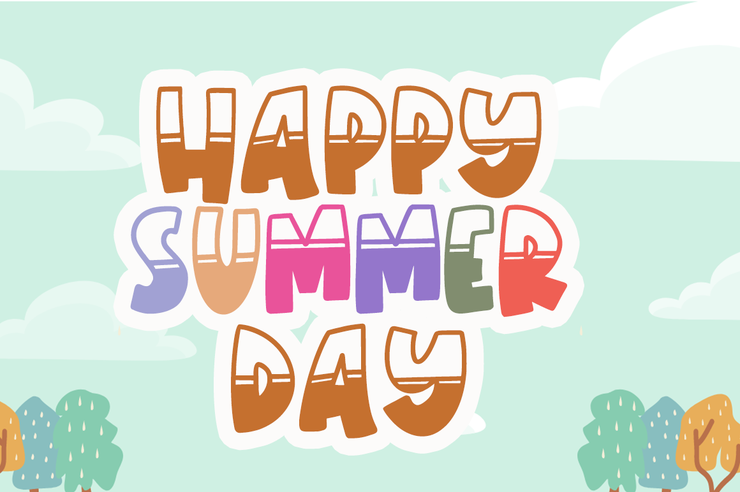
Birthday ist eine lebendige, dekorative englische Schrift mit verspielten Kurven und festlichen, glatten Strichen. Sie verfügt über helle, warme und fröhliche visuelle Effekte, die perfekt zu Geburtstagsfeiern, Jubiläen und fröhlichen Festszenen passen. Diese charmante Schrift ist ideal für Geburtstagseinladungskarten, Partyposter, Geschenkverpackungsetiketten, Grafiken für Konditoreien, Geburtstagsinhalte in sozialen Medien, Veranstaltungsbanner und dekorative Typografie für Feiertage. Komplett mit Groß- und Kleinbuchstaben ist sie hochgradig skalierbar und lässt sich leicht an Farben, Größen und Layouts anpassen, ohne ihre fröhlichen festlichen Details zu verlieren. Geeignet für Grafikdesigner, Partyplaner und kommerzielle Projekte, um warme, lebendige und attraktive visuelle works.Free für den kommerziellen Gebrauch zu schaffen / Kein Copyright 1